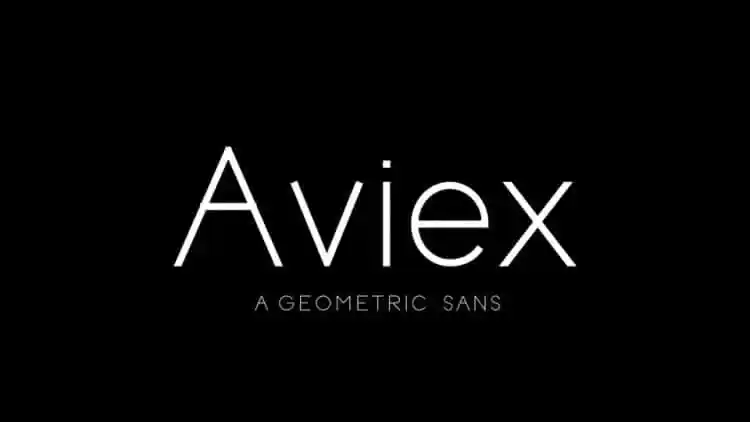
Aviex Sans Serif Font – Fonte Grátis
Aviex Sans Serif Font
A Aviex Sans Serif é uma fonte moderna e nostálgica que oferece um equilíbrio harmonioso entre atualidade e nostalgia. Perfeita para logos, magazines e redes sociais, esta fonte está pronta para combinar bem em suas próximas criações. Se você busca algo elegante, sofisticado e moderno para ilustrar seus projetos, a Aviex Sans Serif é o seu fonte ideal. Para os amantes de estilos clássicos e contemporâneos, esta fonte foi criada com um toque refinado, proporcionando uma combinação perfeita entre elegância e modernidade. Não hesite em experimentar a Aviex Sans Serif para dar vida à sua próxima peça visual, seja ela um logo vibrante ou texto impecavelmente bem-formatado.